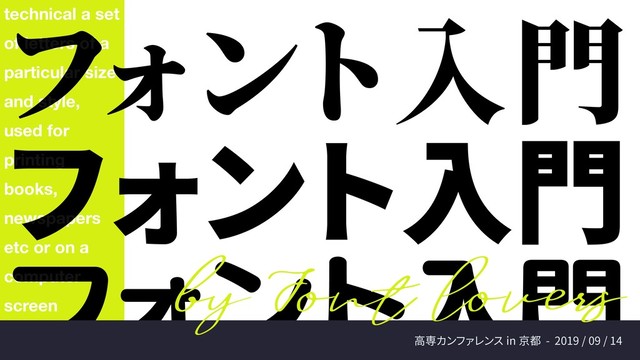
フォント入門 / intro-font
高専カンファレンス in 京都で発表した内容。作ってるうちに「これ入門か……?」となっていたのですがまぁいいでしょう。
1. technical a set of letters of a particular size and
style, used for printing books, newspapers etc or on a computer screen フ ォント入門 フォント入門 ϑΥϯτೖ໳ 高専カンファレンス in 京都 - 2019 / 09 / 14 by Font lovers technical a set of letters of a particular size and style, used for printing books, newspapers etc or on a computer screen
3. 違いを見てみよう。とめやはらいの形、太さの変化、細部に宿る特徴が鍵。 太 さ と め は ら い ウ ロ
コ ︵ セ リ フ ︶ ※ 角 ウ ロ コ と 呼 ば れ て い る 明 朝 体 ゴ シ ッ ク 体
4. 永 MS P明朝 情に棹させば流される。 智に働けば 角が立つ。 どこへ越しても住みにくい と悟った時、 詩が生れて、 画が出来
る。 とかくに人の世は住みにくい。 卒論の定番。リ ョービの「本明朝」を RICOH が PC でみやすいように改変、Windows に導入。無料フ ォン トではない。
5. 永 IPAex 明朝 情に棹させば流される。智に働けば 角が立つ。どこへ越しても住みにく い と悟った時、 詩が生れて、 画が出来る。 とかく
に人の世は住みにく い。 TypeBank 社の TB 明兆(有料)を元に IPA が「誰でも無料に使えるフ ォン トが必要だ」との考えの元制作された。
6. 永 あおぞら明朝 情に棹させば流される。 智に働けば 角が立つ。 どこへ越しても住みにくい と悟った時、 詩が生れて、 画が出来る。 とかくに人の世は住みにくい。
IPA 明朝が改変可能になったことで、有志によ って生み出されたフ ォン ト。 「はんなり明朝」等も同様。7ウェイ ト。
7. 永 源ノ明朝 JP 情に棹させば流される。智に働けば 角が立つ。どこへ越しても住みにくい と悟った時、 詩が生れて、 画が出来る。 とかくに人の世は住みにくい。 Adobe
と Google が共同開発したフリーフ ォン ト。スマホ等の小さな画面でも読みやすいよう設計された。7ウェイ ト。
8. 永 MS ゴシック 情に棹させば流される。智に働けば 角が立つ。どこへ越し ても住みに く い と悟った時、 詩が生れて、
画が出来る。 とかくに人の世は住みに く い。 初めての日本語 TrueType Font。MS 明朝も同様。ビッ トマップからアウ トラインデータへの技術移行がベースにある。
9. 永 メイリオ 情に棹させば流される。智に働けば 角が立つ。どこへ越しても住みに くい と悟った時、 詩が生れて、 画が出来る。 とかくに人の世は住みに くい。
MS ゴシックに代わる、より可読性の高いゴシック体として開発された。 「ClearType」に対応。名前は「明瞭」に由来。
に標準装備の人気書体。フ トコロを少し締めた読みやすいデザイン。京都の地名「柊野」に由来。
the client/server distribution. Times New Roman Nuxt.js is a framework for creating Vue.js applications, you can choose between Universal, Static Generated or Single Page application. Iowan Old Style Roman セリフ / ローマン体 ローマン体の中にも 4~5 つ程分類がある。古いのから新しいのまで色々。 serif(ウロコ)がついている。 Our goal is to create a framework flexible enough that you can use it as a main project base or in addition to your current project based on Node.js. Nuxt.js presets all the configuration needed to make your development of a server-rendered Vue.js Application more enjoyable.
called: nuxt generate. It will build a statically generated Vue.js Application. Franklin Gothic 'SVUJHFS Futura サンセリフ serif がない。歴史的には新しいフ ォン ト。Sans-serif にも 4~5 つ程分類がある。気になる人は調べてみてね。 8FCFMJFWFUIBUPQUJPODPVMECFUIFOFYUCJHTUFQJOUIF EFWFMPQNFOUPG8FC"QQMJDBUJPOTXJUINJDSPTFSWJDFT Furthermore, you can also use Nuxt.js to create single page applications (spa mode) quickly, useful to keep Nuxt features while working on backoffice applications.
" ؙΰγ ο Ϋ 筑紫 A 丸ゴシック 初めてみたとき、こんなに可愛いのに幼く見えないの度肝抜いた。使い所良すぎて脳死で使ってまう。起訴。
$ Φʔ ϧ υ໌ே 筑紫 { A || B || C } オールド明朝 A は王道。B は崩した感じ。C はフ トコロが大き く丸い。印刷とかで使うとよりオシャレ。
͘ ͚ ͜ ͍͋ ͏ ͓͔͖͑ ͘ ͚͜ 筑紫 { A || B || C } オールド明朝 ひらがなで見るとかなり特徴が分かれる。